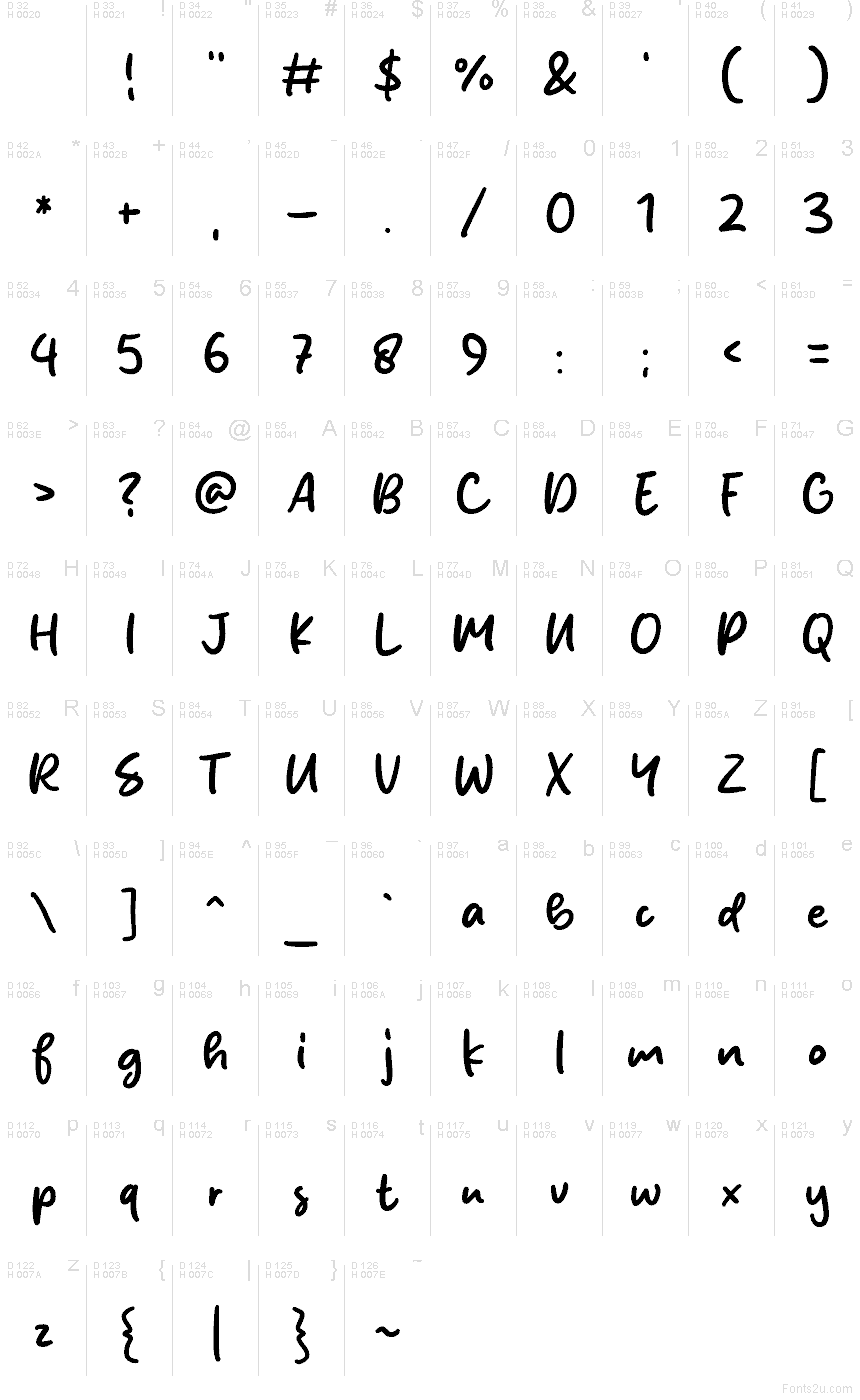
Sunday Drift od MJType je bezplatné ručně psané písmo, které vyniká širokými, plynulými tahy a neformálním rytmem psaným štětcem. Písmena se propojují volným, přirozeným způsobem a díky zaobleným tvarům, měkkým spojům a lehce nepravidelné základní lince působí velmi osobitě a bezprostředně.
Sunday Drift skvěle funguje v logách, citátech, grafice pro sociální sítě, na obalech produktů, pozvánkách i v krátkých nadpisech, kde je potřeba, aby text působil uvolněně a lidsky. Svým zametavým pohybem a neformálními tvary se hodí pro branding ve stylu podpisu, přání, etikety nebo jako výrazný prvek na plakátech.